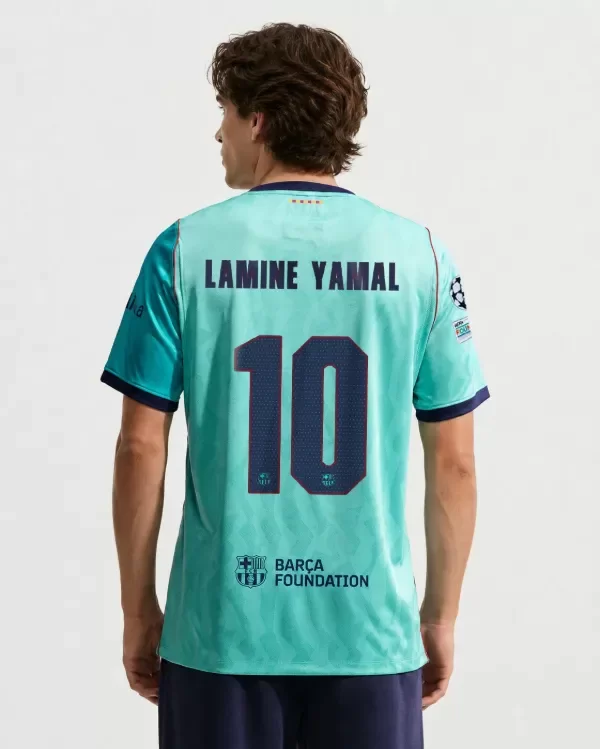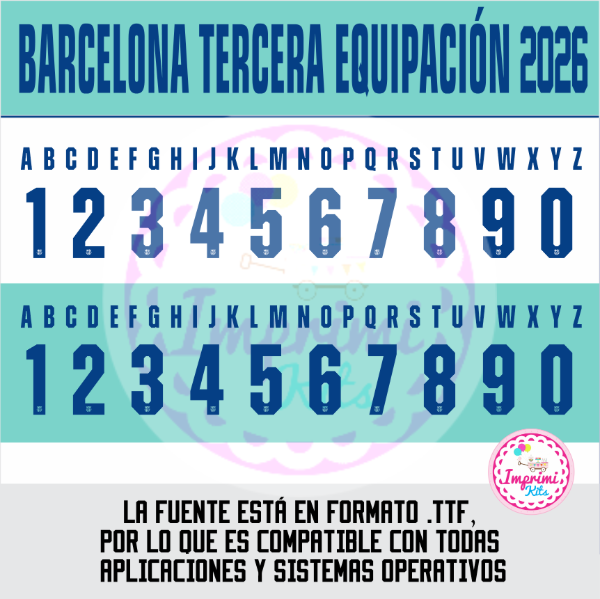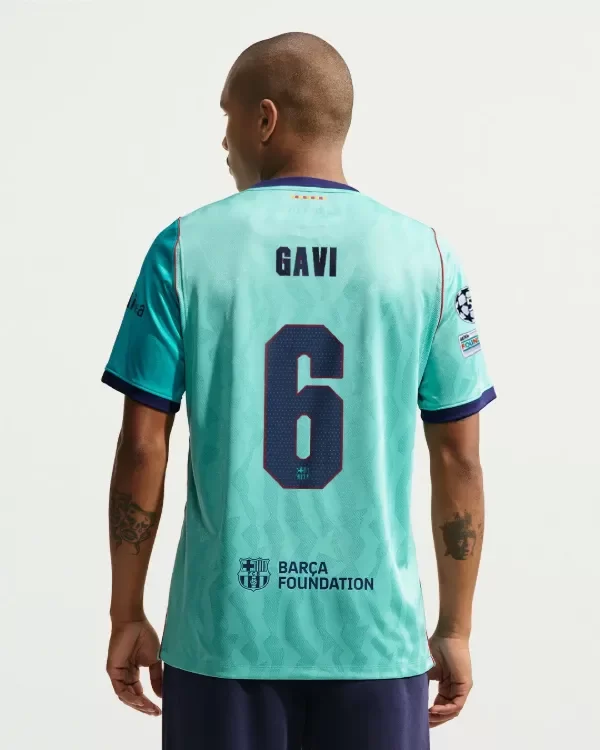
Tipografia Barcelona 2026 2027 Tercera Equipación Camiseta Ttf Otf Numeros Dorsal
Tipografía Números Fuente 2026
Realizá todo tipo de creaciones con la tipografía utilizada actualmente en el club